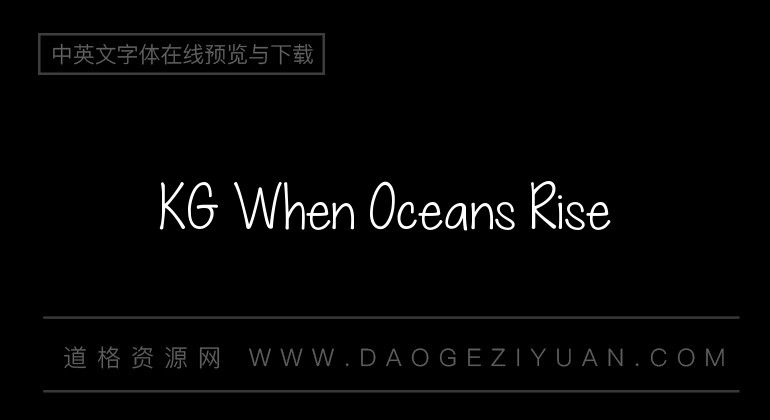
KG When Oceans Rise是一种手写风格的字体,由设计师Kimberly Geswein设计。它的特点是字母的线条不规则、有些毛糙,仿佛是手写的效果。 该字体有两种版本:Regular和Bold。Regular版本的字母较为细小,适合用于段落文本和较小的文字。Bold版本的字母较为粗大,适合用于标题和大字。 KG When Oceans Rise字体的设计灵感来自于一首基督教赞美诗《Oceans (Where Feet May Fail)》。因此,它也常被用于宗教、信仰、灵性等相关领域的设计中。该字体适用于各种设计项目,如海报、招贴、名片、封面等。内容介绍
KG When Oceans Rise是一款非常不错的手写艺术字体,具有很好的视觉感,适合于文化类的宣传设计、商业类品牌的广告和产品包装设计以及个性化文字排版等较多场景。